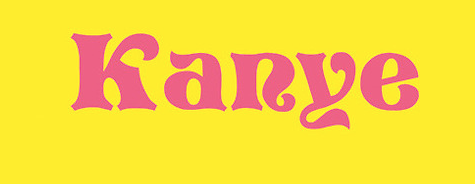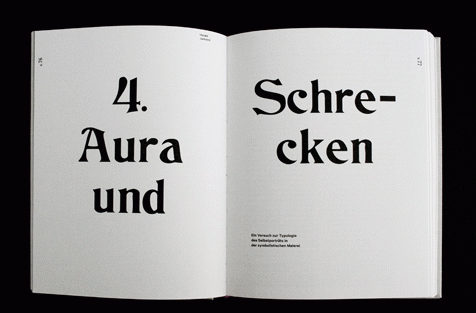
mir ist neuerdings dieser schnipsel untergekommen.
sollte man sie kennen?
Edit: Entweder es gibt noch eine weitere Version, oder die Serifen sind in dem Beispiel modifiziert worden.
Außerdem ist in dem Beispiel der Raum zwischen K und a viel zu groß und irgendjemand hat irgendwann mal das e nicht richtig aufgeklebt. Neigt zu sehr nach rechts. Letzteres kommt öfters vor bei Schriften die in den 50er bis 70er Jahre husch-husch für den Foto-Headlinesatz aufbereitet wurden.
anbei habe ich noch ein beispiel entdeckt welches zu der von mir soeben initiierten gattung der »floralantiquas« gehören könnte. kann jemand diese auch noch beim namen nennen?
ich dachte erst, es sei die cristoforo von thomas phinney. allerdings ist die wohl noch nicht fertig und verfügbar. in wirklichkeit ist es also eine offenbar auf denselben mustern basierende version bei myfonts, deren kurvenqualität allerdings unter aller sau ist (siehe dieses e):
außerdem gibt es noch einen (noch scheußlichereren) freefont namens ›columbus‹.